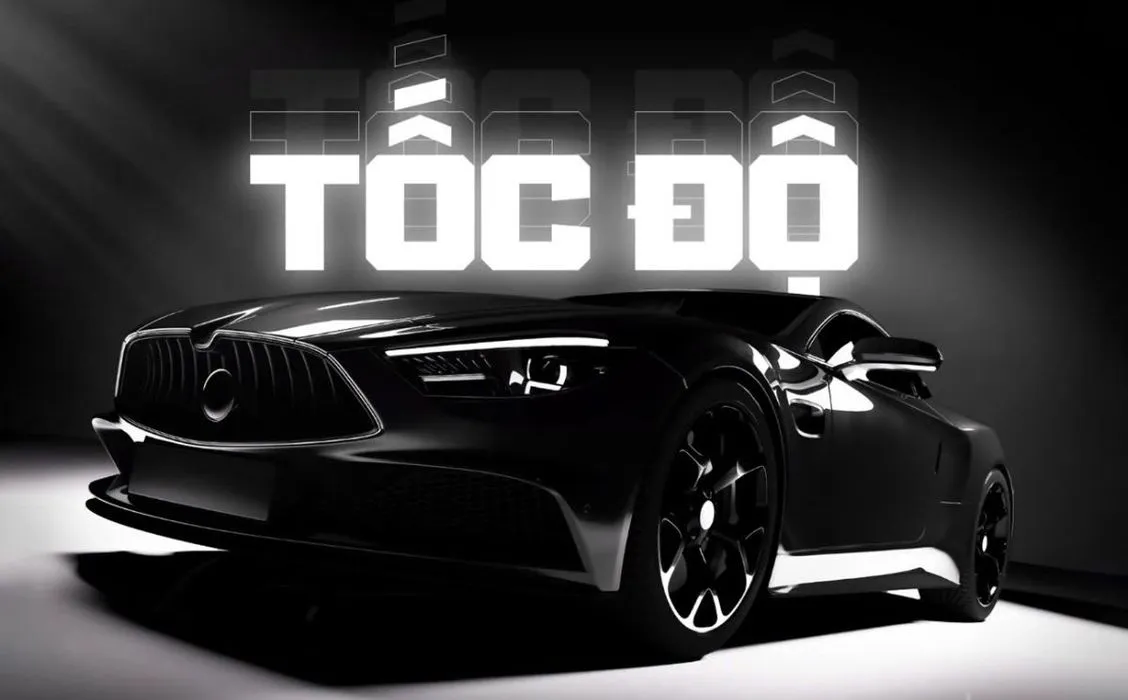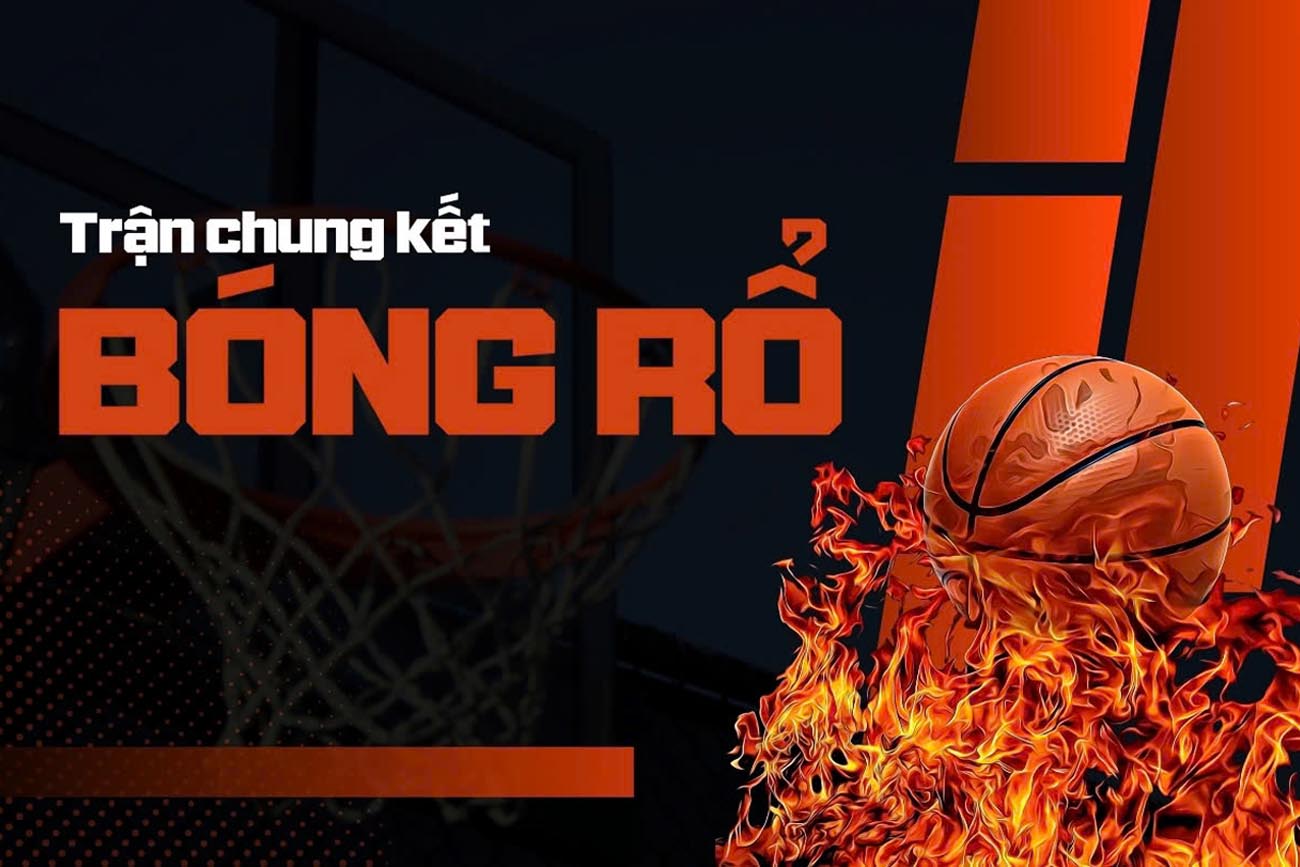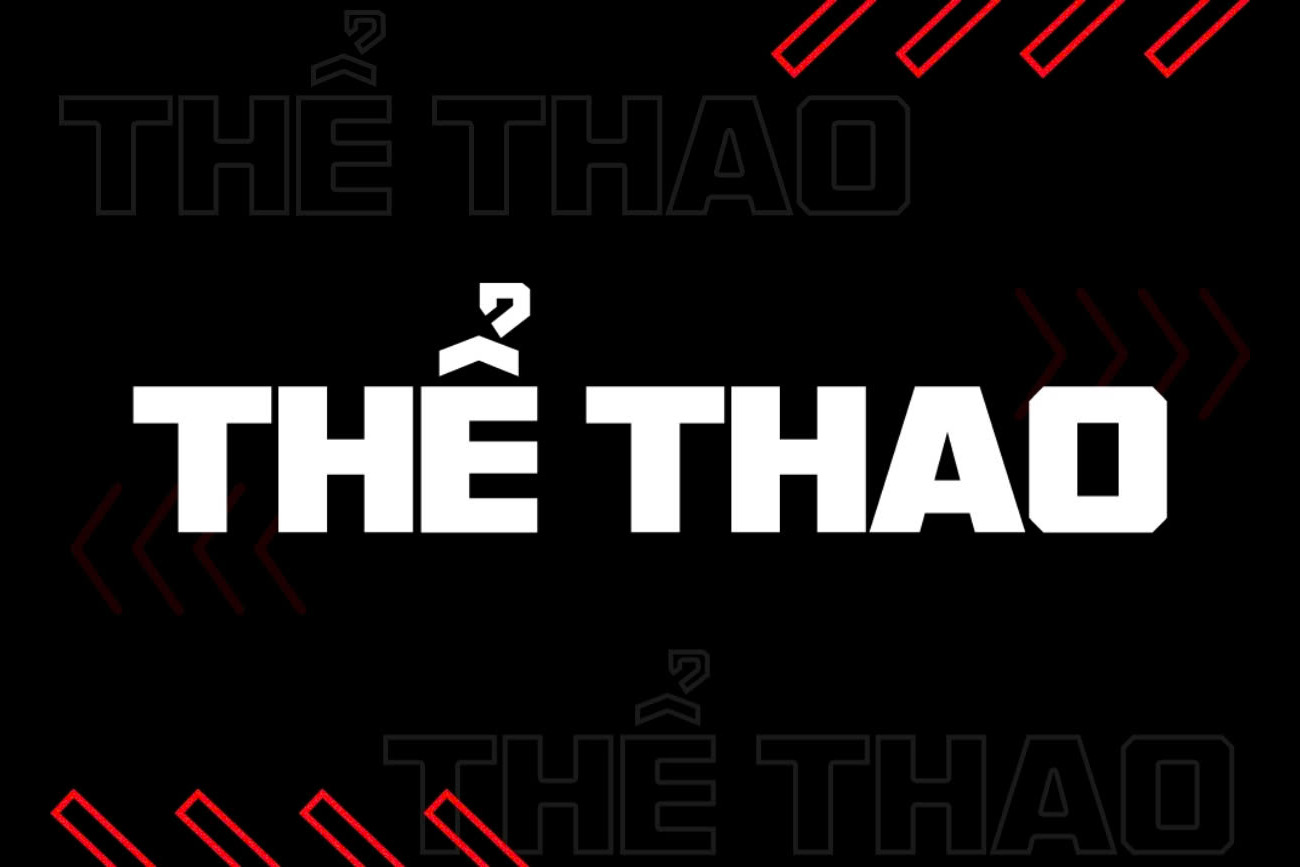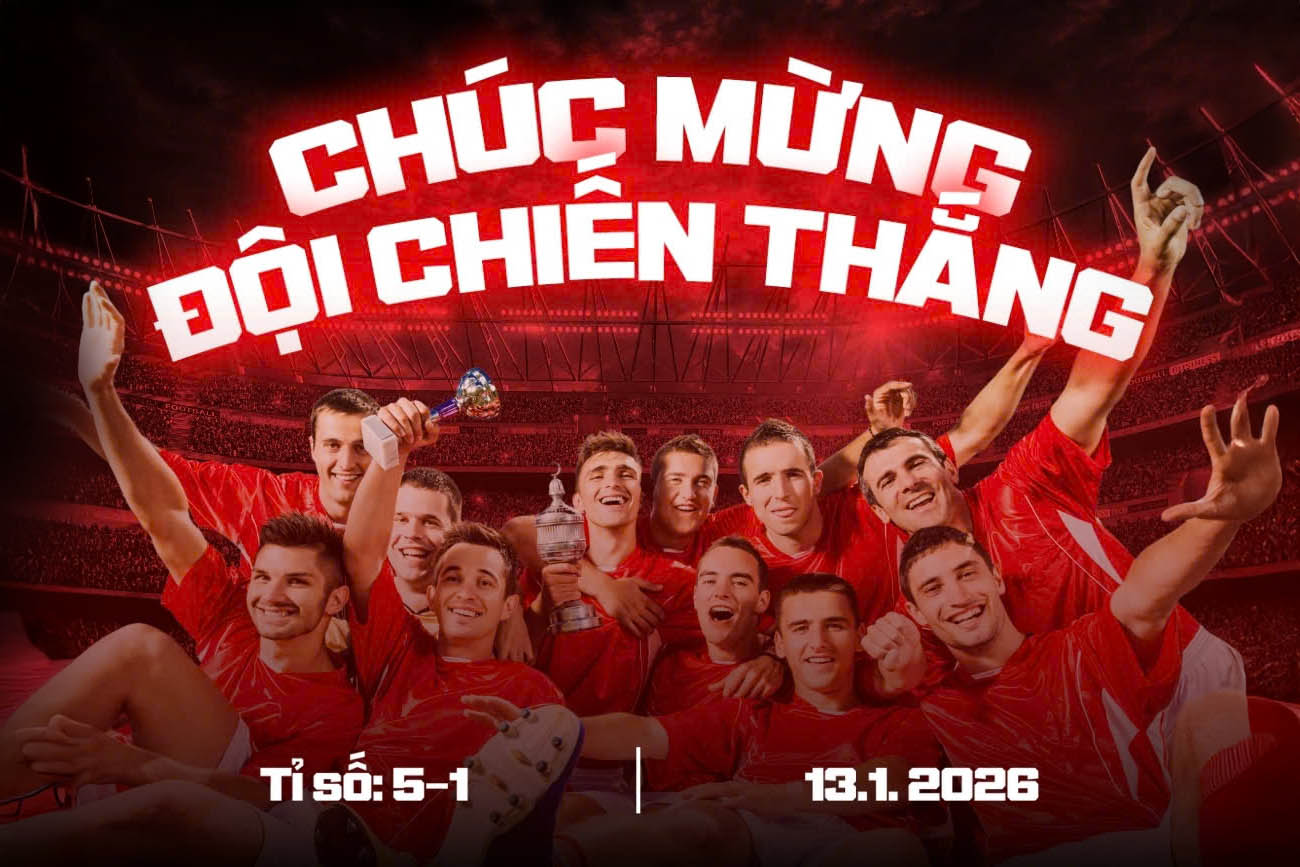
Nếu bạn đang tìm kiếm một giải pháp typography để truyền tải trọn vẹn tinh thần tốc độ, năng động và đầy quyền lực, TH Bringas Việt hóa chính là câu trả lời hoàn hảo. Thuộc dòng font chữ chuyên dụng cho mảng thể thao, bộ font này sở hữu những đường nét vững chãi, góc cạnh và mang tính bứt phá cao, sẵn sàng làm bừng sáng mọi ý tưởng thiết kế của bạn.
Ngôn ngữ thiết kế đậm chất cơ bắp: Với cấu trúc chữ dày dặn, các góc bo tròn kết hợp với những đường cắt vát dứt khoát, font chữ tạo nên cảm giác kiên định, vững chãi và tràn đầy năng lượng.
Vũ khí tối thượng cho Sport & Streetwear: Là lựa chọn xuất sắc để làm tiêu đề game, logo câu lạc bộ thể thao, số áo thi đấu, hoặc các ấn phẩm truyền thông, poster quảng cáo cho các thương hiệu thời trang đường phố, gym và fitness.
Việt hóa hoàn chỉnh, hiển thị sắc nét: Bản Việt hóa được chăm chút tỉ mỉ từng dấu câu, cân chỉnh khoảng cách (kerning) tối ưu, giúp các khối văn bản tiếng Việt hiển thị mượt mà, đồng bộ mà không làm mất đi phom dáng mạnh mẽ nguyên bản.
TH Bringas sẽ là dấu ấn định hình phong cách, giúp thông điệp truyền thông của bạn trở nên sống động, uy lực và dễ dàng găm sâu vào tâm trí người xem.